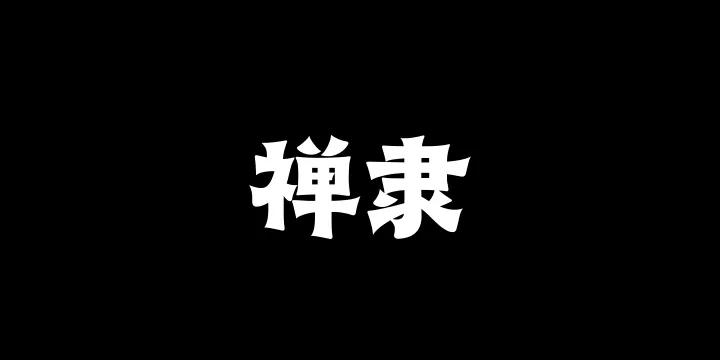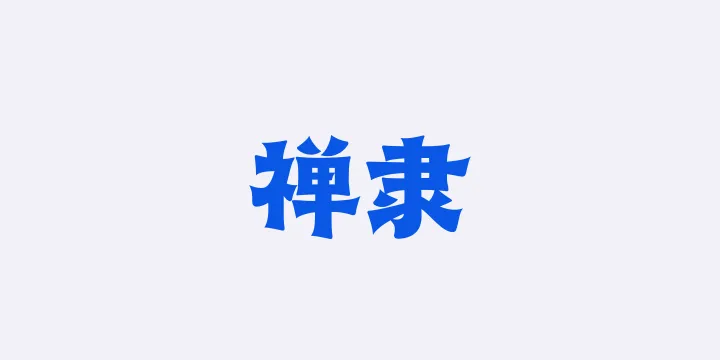
山海禅隶W By 山海字库 商用字体
字体全名: 山海禅隶W
字体简介: 山海禅隶,是一款全新隶书风格的字体,包含汉字9169个,符号200+个。该字体是一款具有强劲视觉冲击力的隶书风格的字体,字形结构多为方形结构,如正方形、长方形或扁方形,强调字形的稳定性和内敛精神。字形大小悬殊,通过大小不一的字来形成对比和层次感,直线与曲线的完美结合,使造型硬朗的同时兼具圆润柔美的特点。